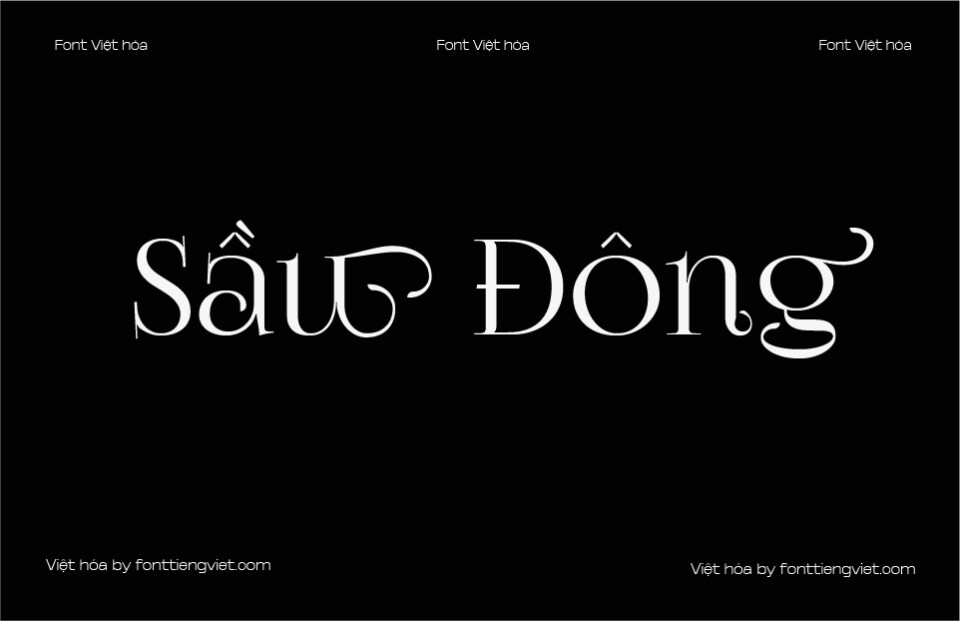
Font Việt hóa 1FTV VIP Foglihten
Giới thiệu về Font Việt hóa 1FTV VIP Foglihten
Trong thế giới đồ họa hiện đại, việc tìm kiếm một bộ Font Miễn Phí chất lượng cao và phù hợp với tiếng Việt luôn là ưu tiên hàng đầu của các nhà thiết kế. Font Việt hóa 1FTV VIP Foglihten nổi lên như một hiện tượng nhờ sự kết hợp hoàn mỹ giữa nét cổ điển và hơi thở đương đại. Đây là bộ font chữ thuộc phong cách Serif (có chân) với các đường nét thanh mảnh, uốn lượn tinh tế, mang lại cảm giác xa hoa và quyền quý cho mọi ấn phẩm. Phiên bản 1FTV VIP không chỉ dừng lại ở việc chuyển ngữ mà còn được tinh chỉnh kỹ lưỡng về dấu câu, đảm bảo tính thẩm mỹ cao nhất khi gõ văn bản tiếng Việt mà không gặp lỗi hiển thị.
Đặc điểm nổi bật của bộ Font Việt hóa 1FTV VIP Foglihten
Thiết kế nghệ thuật và bay bổng
Điểm làm nên sự khác biệt của Font Việt hóa 1FTV VIP Foglihten chính là các ký tự thay thế (alternates) và các nét móc nối (ligatures) vô cùng phong phú. Mỗi chữ cái được tạo hình như một tác phẩm nghệ thuật, giúp người dùng dễ dàng tạo ra những tiêu đề ấn tượng mà không cần quá nhiều kỹ năng xử lý đồ họa phức tạp. Các đường cong mềm mại của bộ font này cực kỳ phù hợp cho các chủ đề về làm đẹp, thời trang cao cấp hoặc thiệp mời sự kiện sang trọng.
Khả năng ứng dụng đa dạng trong thực tế
Dù mang phong cách nghệ thuật đậm nét, Font Việt hóa 1FTV VIP Foglihten vẫn giữ được độ đọc tốt ở nhiều kích thước khác nhau. Bạn có thể sử dụng bộ font này cho thiết kế logo thương hiệu, dàn trang bìa tạp chí, hay thậm chí là tạo ra những trích dẫn (quote) đầy cảm hứng trên mạng xã hội. Đối với các bạn học sinh và sinh viên, đây là công cụ đắc lực để làm nổi bật các bài thuyết trình hoặc dự án sáng tạo cá nhân, giúp sản phẩm trở nên chuyên nghiệp và bắt mắt hơn trong mắt thầy cô và bạn bè.
Lý do bạn nên sở hữu Font Việt hóa 1FTV VIP Foglihten
Việc lựa chọn Font Việt hóa 1FTV VIP Foglihten mang lại nhiều lợi ích thiết thực cho người dùng Việt. Thứ nhất, bộ font này đã được tối ưu hóa hoàn toàn cho bảng mã Unicode, giúp gõ tiếng Việt mượt mà trên tất cả các phần mềm thiết kế như Photoshop, AI, hay Canva. Thứ hai, đây là phiên bản VIP được chăm chút về khoảng cách chữ (kerning), giúp bố cục văn bản luôn cân đối và hài hòa. Thay vì sử dụng những font chữ mặc định nhàm chán, việc thay đổi sang bộ font này sẽ tạo ra một cú hích lớn về mặt thị giác cho người xem.
Để tận dụng tối đa vẻ đẹp của Font Việt hóa 1FTV VIP Foglihten, bạn nên kết hợp nó với các font chữ không chân (Sans-serif) đơn giản cho phần nội dung văn bản. Sự tương phản giữa nét cầu kỳ của Foglihten ở tiêu đề và nét hiện đại của font phụ sẽ tạo nên một tổng thể thiết kế đẳng cấp. Sau khi tải về, bạn chỉ cần giải nén và cài đặt trực tiếp vào hệ thống máy tính để bắt đầu sáng tạo. Đừng quên thử nghiệm với các tính năng OpenType để khám phá hết các ký tự trang trí ẩn bên trong bộ font tuyệt vời này.
Kết luận về bộ font đẳng cấp này
Hy vọng rằng bộ Font Việt hóa 1FTV VIP Foglihten sẽ trở thành nguồn cảm hứng mới cho các dự án thiết kế sắp tới của bạn. Với sự kết hợp giữa nét chữ uyển chuyển và khả năng hỗ trợ tiếng Việt hoàn hảo, đây chắc chắn là lựa chọn không thể bỏ qua trong bộ sưu tập font chữ cá nhân. Nếu bạn đang tìm kiếm thêm nhiều tài nguyên đồ họa chất lượng, hãy thường xuyên ghé thăm trang Font Miễn Phí, Font Việt Hóa, Font Việt hóa 1FTV VIP Foglihten để cập nhật những xu hướng thiết kế mới nhất và tải về những bộ font độc đáo hoàn toàn miễn phí nhé.